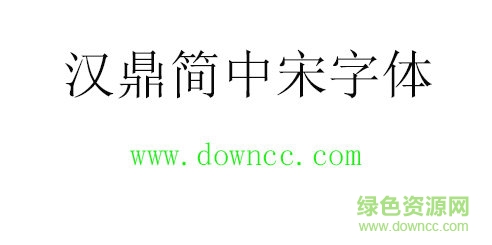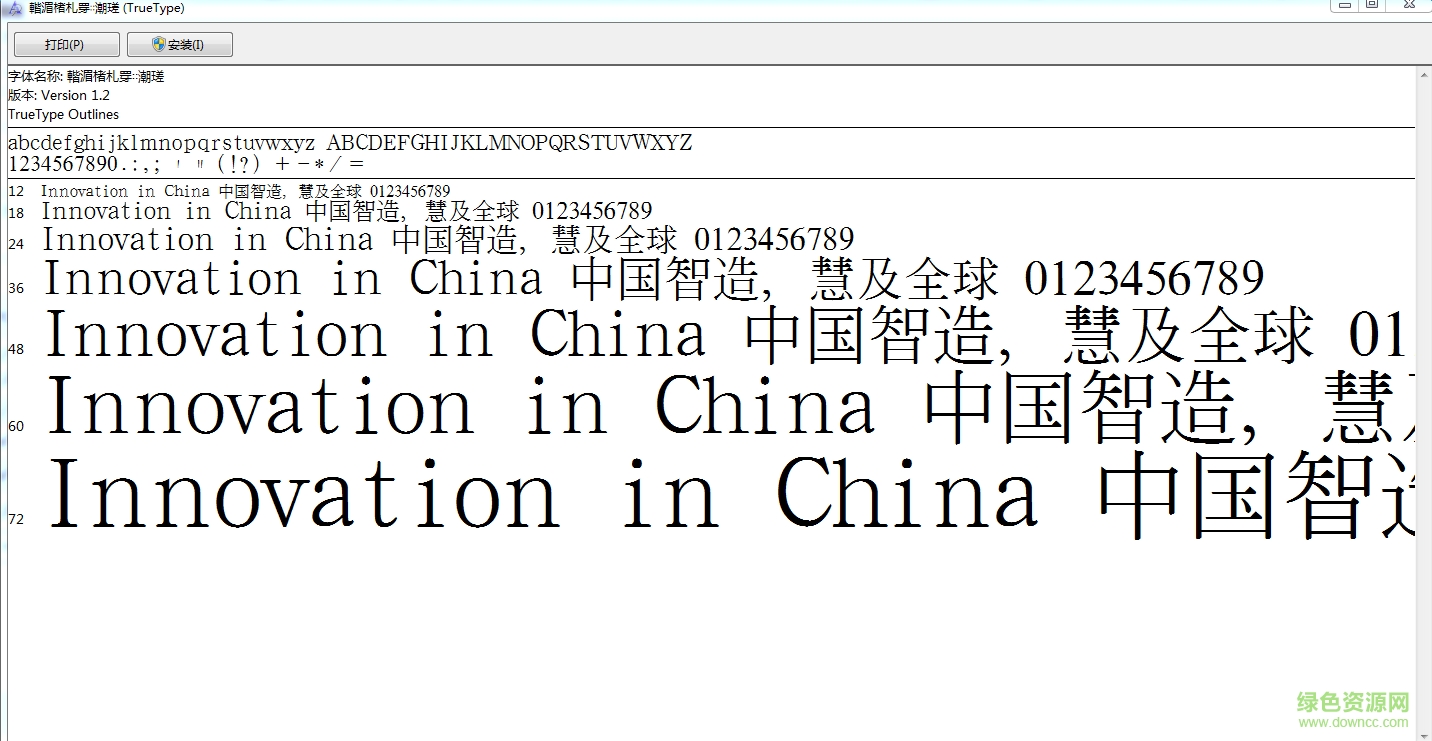
漢鼎簡中宋體是一款應(yīng)用于平面設(shè)計、文學(xué)創(chuàng)作、平面廣告等領(lǐng)域的漢鼎字體,字體結(jié)構(gòu)勻稱,字形神韻超逸,非常適合朋友們在創(chuàng)作書法內(nèi)容的時候使用,而且還是永久免費的哦,但是只限于個人使用,喜歡的小伙伴趕緊下載收藏吧!